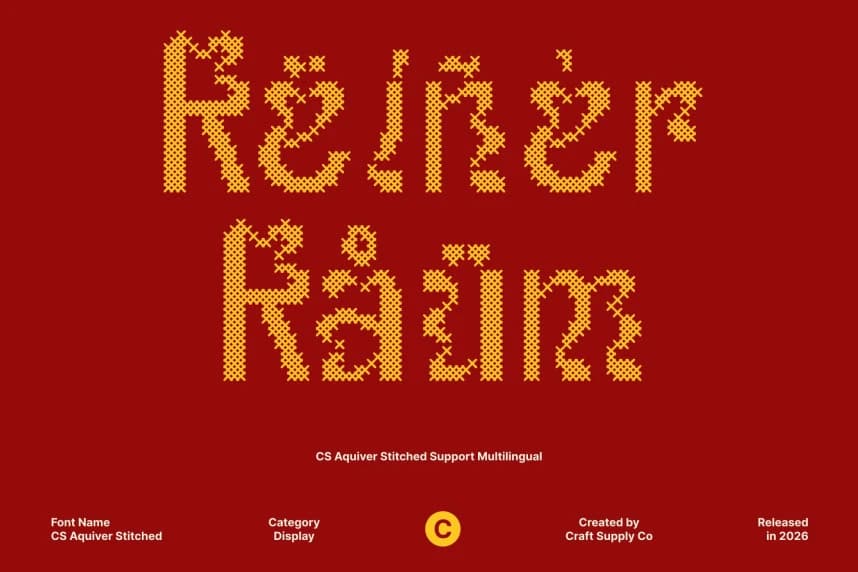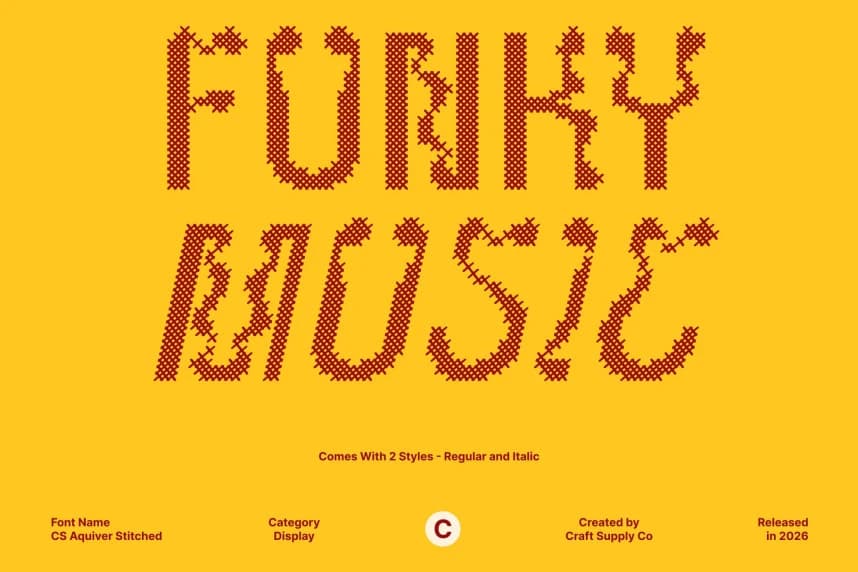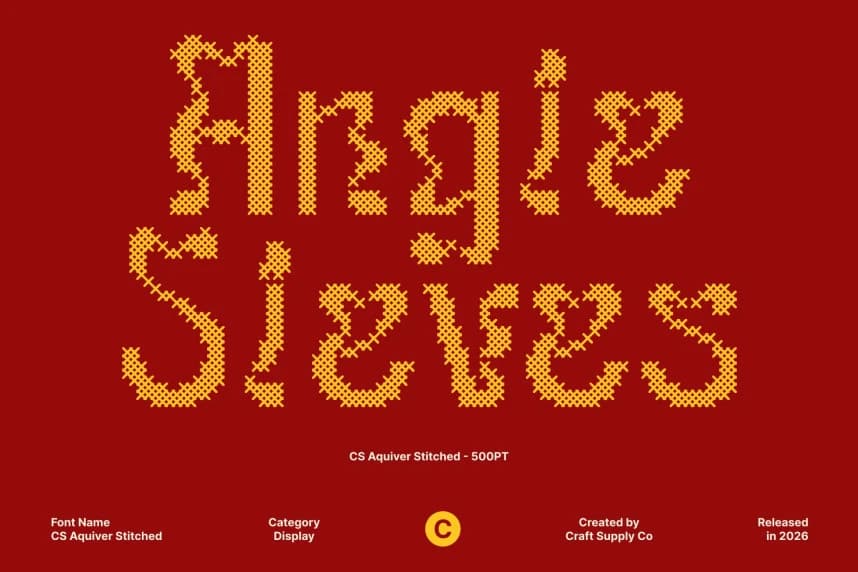
CS Aquiver Dikişli Yazı Tipi
CS Aquiver Stitched Font – Psikedelik Gösterim Yazı Tipi: Kalın Psikedelik Enerji, El Yapımı Doku ile. Bu, cesur ve ifade dolu harf biçimlerine sahip, gerçeküstü karakterlerle dolu canlı bir psikedelik gösterim yazı tipidir.
CS Aquiver Stitched Font – Psikedelik Gösterim Yazı Tipi, Kalın; El Yapımı Doku ile Psikedelik Enerji. Bu, cesur, ifade gücü yüksek harf biçimlerine sahip canlı bir psikedelik gösterim yazı tipidir ve trippy karakterlerle doludur.